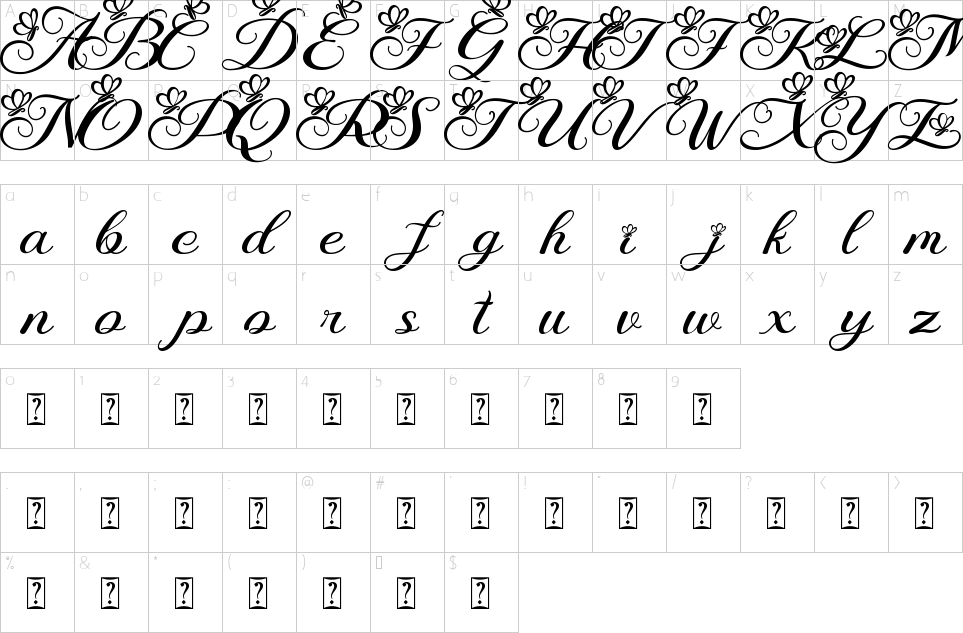
Agetya Butterfly Font – Download Grátis
A fonte Agetya Butterfly oferece uma experiência visual sofisticada e envolvente, projetada especialmente para quem busca uma fonte de alta qualidade para seus projetos de design. Sua forma delicada e elegante remete à serenidade das borboletas, simbolizando a tranquilidade e a beleza da natureza. Agetya Butterfly é perfeita para criações que exigem um toque delicado e sofisticado, seja em design gráfico, escrita para revistas ou qualquer outro aplicativo visual. Esta fonte foi criada por Yoga Letter, e já foi baixada 566 vezes, testemunhando a sua qualidade e beleza. Com Agetya Butterfly, você pode adicionar um toque especial e único a seus projetos.